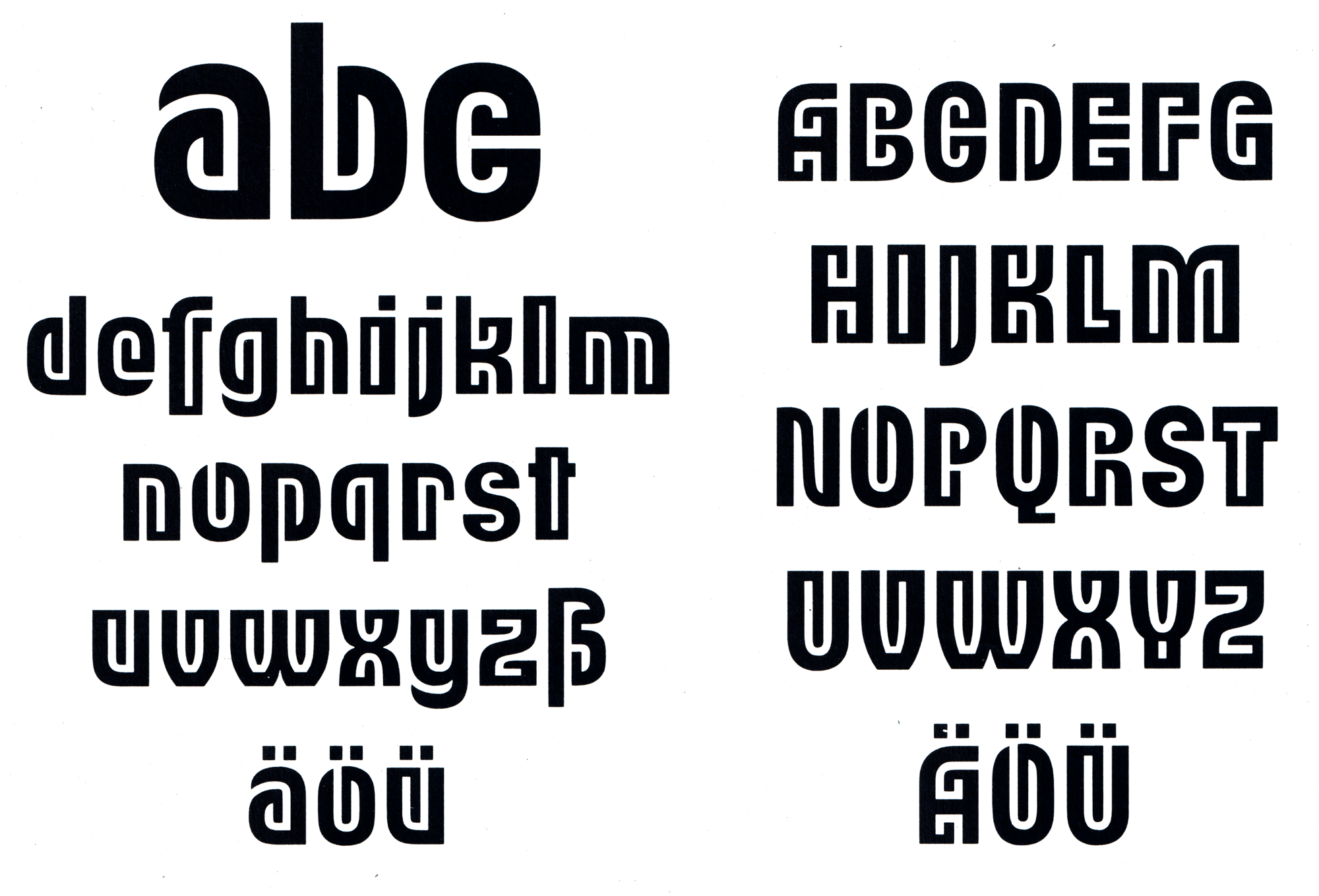
- circa 1988
- Antiqua dekorativ
Der Grafiker Erhard Kaiser beteiligte sich mit insgesamt sieben Beiträgen an einem Ideenwettbewerb für neue Auszeichnungsschriften 1985 und erhielt für seine Schrift Kleopatra den ersten Preis. Maßgebend für das Urteil der Jury war die Tatsache, dass es sich hierbei um eine bisher nicht veröffentlichte Gestaltungsidee handelte, die mit Phantasie und Gefühl für die grafischen Eigenheiten der Schrift ausgeführt ist.
Die Schrift erschien bei Typoart in einem Schnitt im Fotosatz als Schaugrößenversion und wurde von Elsner+Flake als digitale Schrift (2008, Kleopatra Now) aufgelegt.